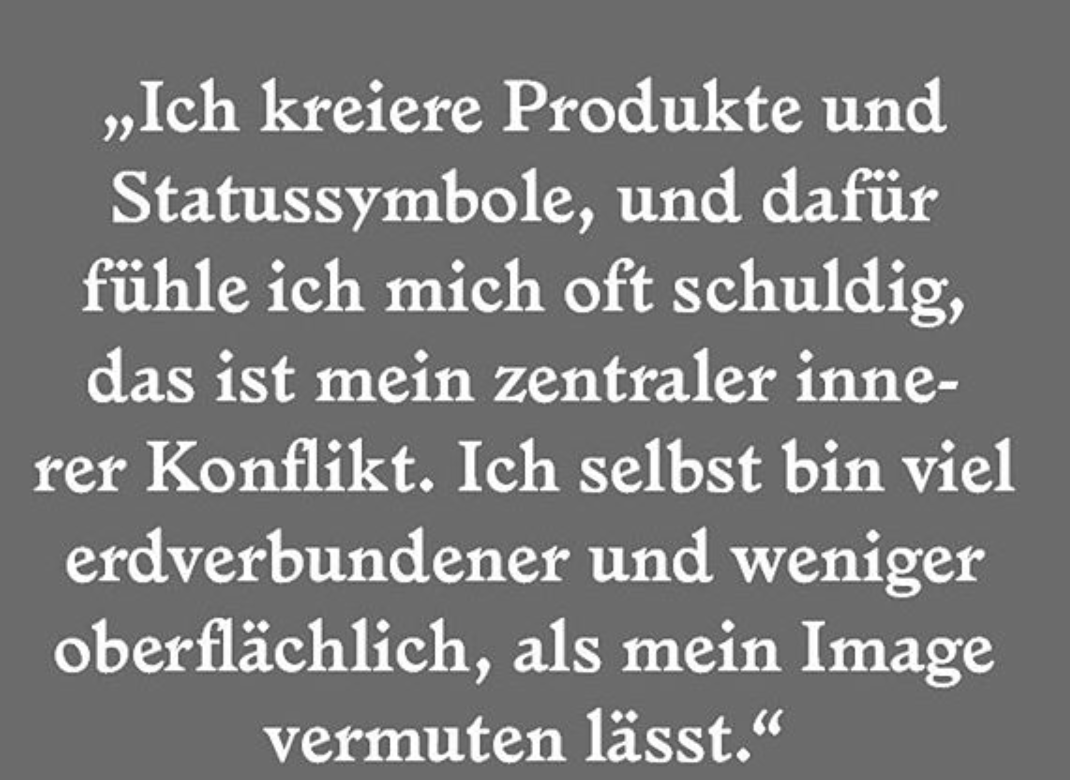
Schrift der Monopol-Zitate gesucht
kennt jemand diese Schrift, in der die Monopol die Zitate auf Instagram setzt?
Das ist die Alte Larish.
Chapeau! Ich habe auch eine Weile gesucht (und kenne jetzt viele Varianten der JENSON) – leider ohne Erfolg. Wie hast Du die ermittelt? Im PDF nachgesehen?
Bei derlei extrovertierten Entwürfen gibt es eine handvoll Entwerfer bzw. Foundries, die mir spontan in den Sinn kommen – Radim Peško ist einer davon.